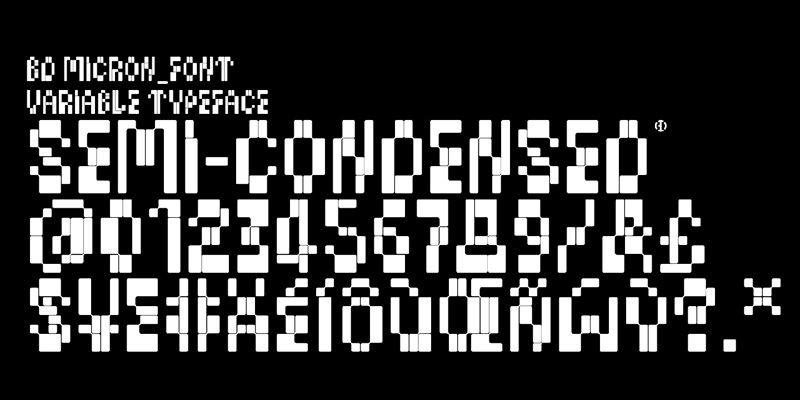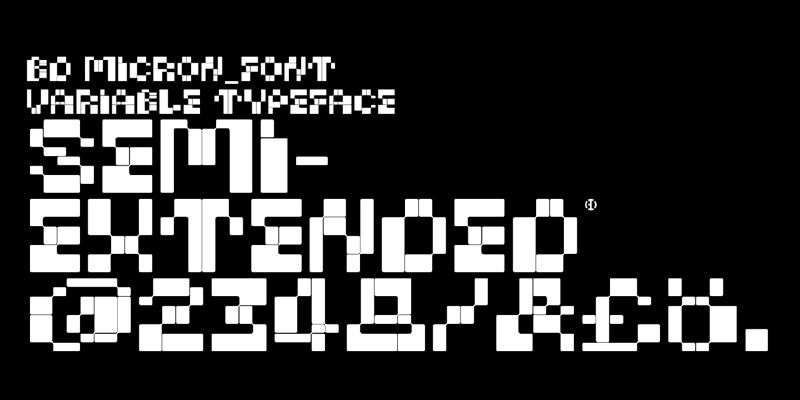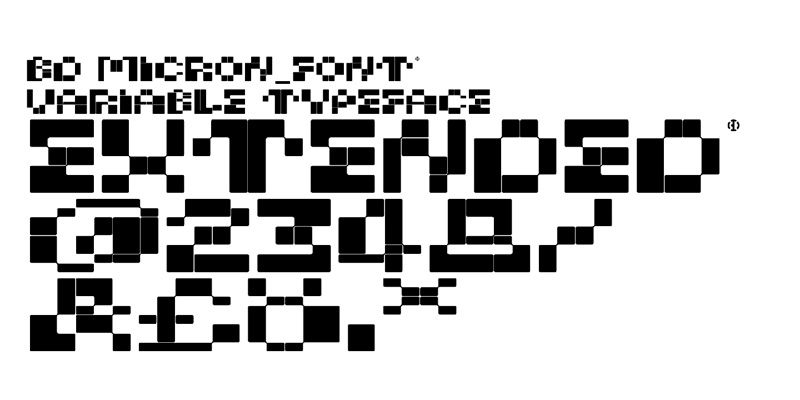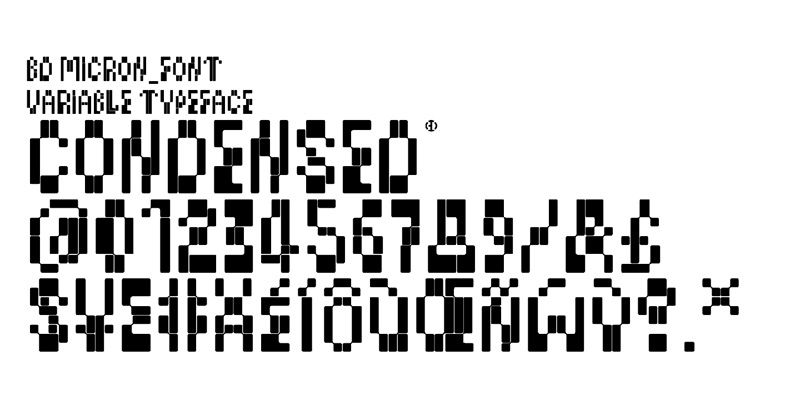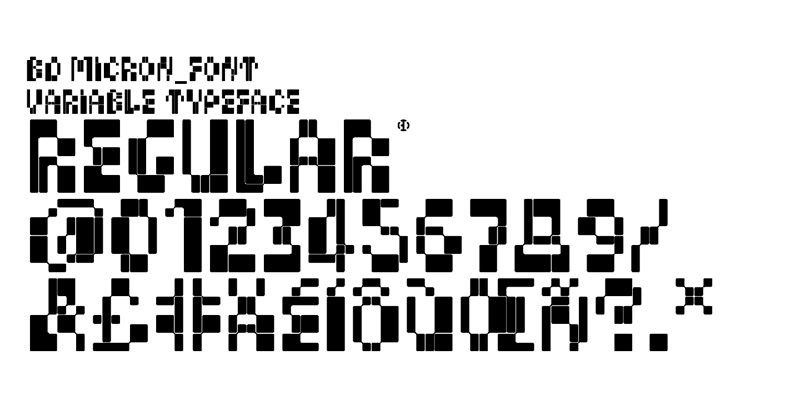
BD Micron Font ist eine technisch anmutende Schrift, die sich hervorragend für den Einsatz in Projekten mit Bezug zu Sci-Fi, Wissenschaft und elektronischer Musik eignet. Entworfen von H1 & Lopetz im Jahr 2019.